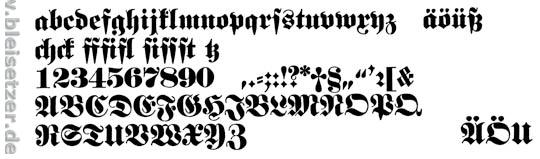
Fette Fraktur - Restaurantflyer ?
für ein prospekt, wollen die leute die fette fraktur, als titelschrift...
es ist ein ländliches, gemütliches restaurant..
weiss jemand eine passende schrift dazu.. für den grundtext.. sollte natürlich nicht zu speziell sein, was einfaches
Dazu paßt natürlich eine „Normal-Fraktur“ also ein magerer Schnitt.
Falls es keine gebrochene sein soll: oft mischen sich damit klassizistische Antiquas (Walbaum, Didot, Prillwitz usw.) recht gefällig.
Dazu paßt natürlich eine „Normal-Fraktur“ …
Ansonsten lieber eine Antiqua oder Grotesk als Kontrastschrift.
Übrigens gibt es viele fette Frakturschriften, die viel, viel schöner sind als die »Fette Fraktur«.
sollte aber lieber ne gut leserliche schrift sein...
So ein Gastronom ist ja vom Umsatz abhängig wie alle.
Über eine Titelzeile in der Fetten Fraktur kann man trefflich streiten - letztendlich Geschmacksache.
Aber die Grundtexte würde ich nicht in einer Gebrochenen setzen...
Setzt man sie korrekt (was sonst?) würden viele Gäste sie nicht lesen können. Setzt man sie... ich mag das gar nicht schreiben... Ihr wißt schon, ausschließlich mit Rund-s... würde ich, wäre ich dort Gast, mir den Wirt holen und, wenn überhaupt, Bratkartoffeln mit Spiegelei bestellen.
So eine Klassizistische, z.B. die Walbaum oder die Didot, finde ich da tatsächlich viel gefälliger, wie der Kollege ja schon schrieb.
Setzt man sie korrekt (was sonst?) würden viele Gäste sie nicht lesen können.
Man sollte die Menschen nicht unterschätzen … und wer nicht lesen kann, hat (zumeist) die Möglichkeit sich verbal zu erkundigen …
Setzt man sie korrekt (was sonst?) würden viele Gäste sie nicht lesen können.
Man sollte die Menschen nicht unterschätzen … und wer nicht lesen kann, hat (zumeist) die Möglichkeit sich verbal zu erkundigen …
Vor einigen Jahren war ich einmal mit Gästen in einem guten Restaurant essen, die, aus welchen Gründen auch immer, ihre Speisekarte auf französisch anbot. Ich beherrsche diese Sprache nicht. Habe also weder verstanden, was dort angeboten wurde, noch hätte ich es aussprechen können. Mich verbal zu erkundigen, hätte ich als... nein, das hätte ich nicht gemacht. Also habe ich dasselbe bestellt wie einer meiner Gäste, der die Sprache beherrschte. Ich werde dort nie wieder essen gehen. Soviel zum Thema "man kann sich ja erkundigen".
Ein Gastronom ist in noch höherem Maße als wir Dienstleister. Er will und soll dem Gast eine Freude bereiten, u.a. mit gutem Essen, aber auch das ganze Drumherum ist wichtig, damit der Gast sich wohlfühlt.
Gibst Du dem Gast eine Speisekarte in die Hand, in der er das Gemeine-(Lang-)s als Gemeines-f ansieht und viele Versalien gar nicht erkennen kann, verunsicherst Du ihn. Er kommt sich ungebildet vor, empfindet ein Nachfragen als Eingestehen eines Mangels an Bildung.
Aber vielleicht schmeckt's ihm ja trotzdem.
Ich bleibe dabei: Gebrochene Schriften über die Überschrift hinaus würde ich vermeiden.
Was ist die Moral der Geschichte, wenn Du ein Erfolgserlebnis gehabt hättest würdest Du wieder hingehen.
Aber das mit dem Französisch ist kein Vergleich. Wenn ich nach Österreich fahre, muß ich mich dort auch immer erkundigen, was sich den hinter den wohlklingenden deutschen Wörtern verbirgt. Im Palatschinken ist nun mal kein Schinken, da hilft die Antiqua auch nicht weiter.
Georg hat recht. Auch wenn ich z.B. korrekt gesetzte Fraktur lesen kann, empfände ich eine durchgängig so gestaltete Speisekarte als überheblich. Genauso geht es mir, wenn hierzulande eine deutsche "Untertitelung" fehlt, auch wenn ich mich mit etwa einem halben Dutzend Sprachen durch Speisekarten hindurchmanövrieren kann. Ich erwarte in einem Restaurant, dass man auf mich als Gast zugeht, und nicht, dass ich mich irgendwie "anpassen" muss. Und mit "richtiger" Fraktur erreicht man halt nur eine Minderheit.
Was ist die Moral der Geschichte, wenn Du ein Erfolgserlebnis gehabt hättest würdest Du wieder hingehen.
Richtig.
Es war aber kein Erfolgserlebnis.
Und ich bin da keine Ausnahme, denn es gibt mehr Menschen in Deutschland, die kein Französisch sprechen als Menschen, die Französisch sprechen.
Schlußfolgerung:
Das wird dem Gastronom ebenfalls bekannt sein. Also läßt sich mit an Sicherheit grenzender Wahrscheinlichkeit vermuten, daß er die Speisekarten bewußt in französischer Sprache abfaßt.
Er versucht also, sich in einem Nischenmarkt zu etablieren.
Das kann gut gehen und ist heutzutage eine kluge Taktik.
Sein Nischenmarkt: Gäste, die gern gut essen und die die französische Sprache beherrschen, gibt es sicher mehr als genug, um von ihren Bewirtungen gut leben zu können.
Übertragen auf unser konkretes Beispiel bedeutet das:
Gibt es genug Gäste, die in einem Restaurant eine Speisekarte lesen können, die einen Gebrochenen Fließtext lesen kann?
aus der neuzeit, bis ich ein altes schriftmuster von 1933 in den händen hielt.
Gibt es genug Gäste, die in einem Restaurant eine Speisekarte lesen können, die einen Gebrochenen Fließtext lesen kann?
Ich bezweifle das.
Übrigens: Es sind ja nicht nur die Leser, die mit Farktur nicht umzugehen wissen. Bei oder in Wurzen passiert man einen verfallenen Gasthof, der an der Façade mit der Frakturschrift »Zux Waage« wirbt. Habe leider jetzt kein Photo davon auf meiner Festplatte gefunden.